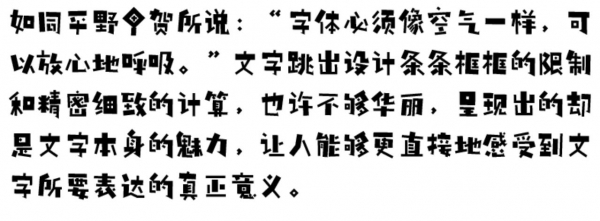
甲贺奇怪01GB演示版字体是由极字和风字库推出的一款比较新颖的黑体,该字体中和了平野甲贺先生本人强烈的个人风格,每个字均有重点笔画,一呼一吸,笔画韵律感极强,竖排横排时均富有设计感,并且具有几何设计感,可以很好的应用于文本装潢、信息展示、网页设计、篆刻制模、数据制作、装潢设计、计算艺术设计、视觉设计、字帖等一切合法应用场景,有喜欢的朋友可免费下载收藏。